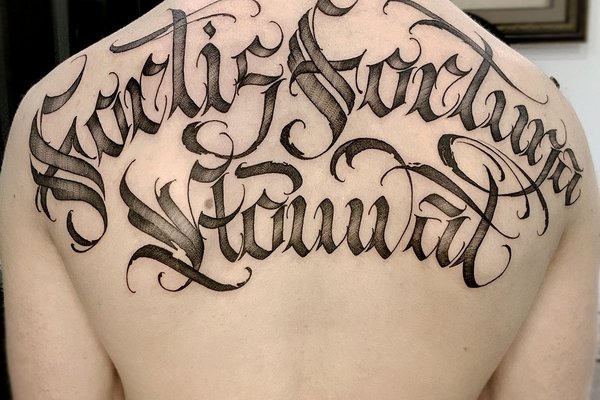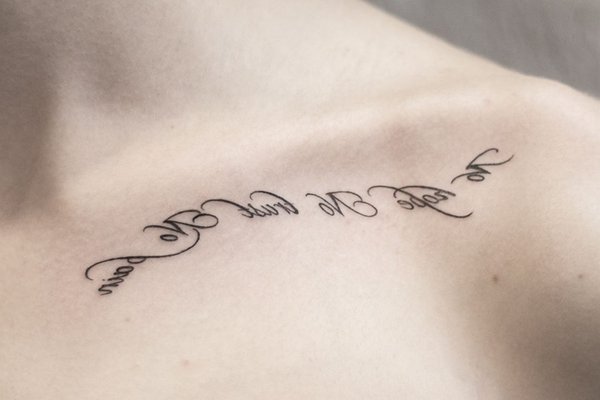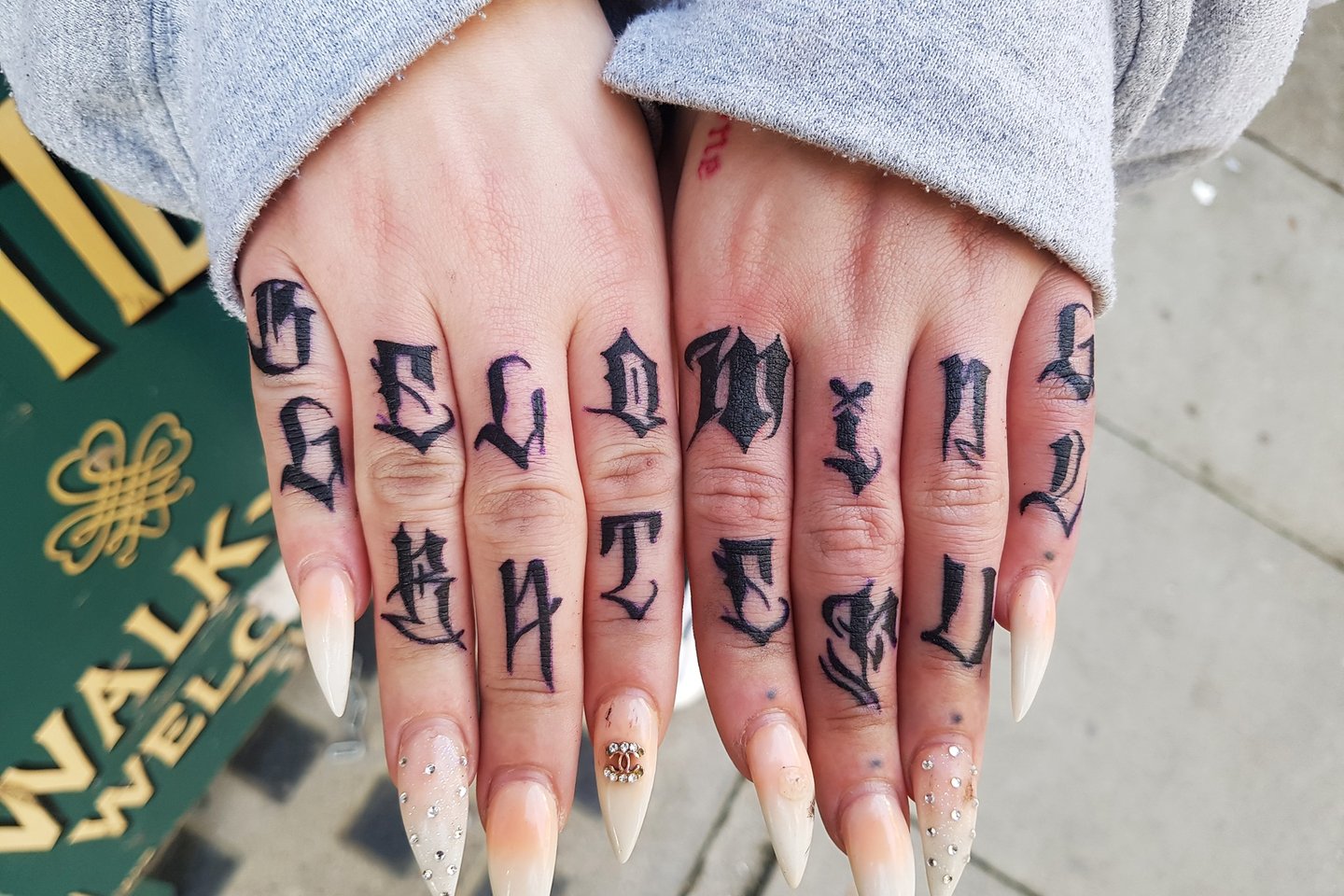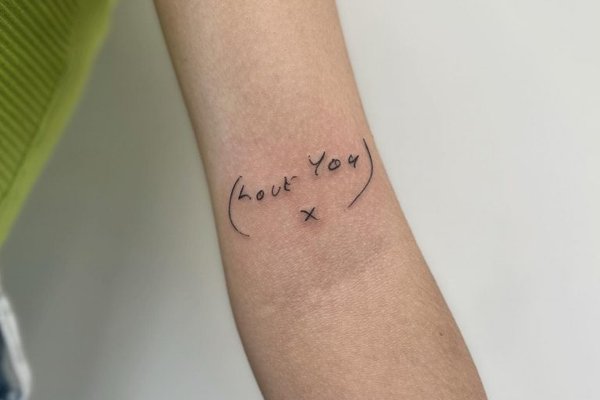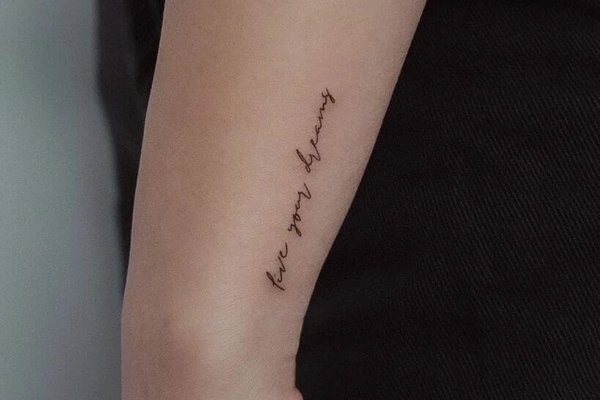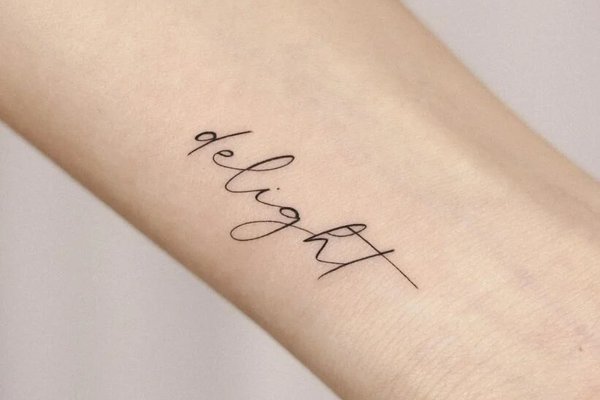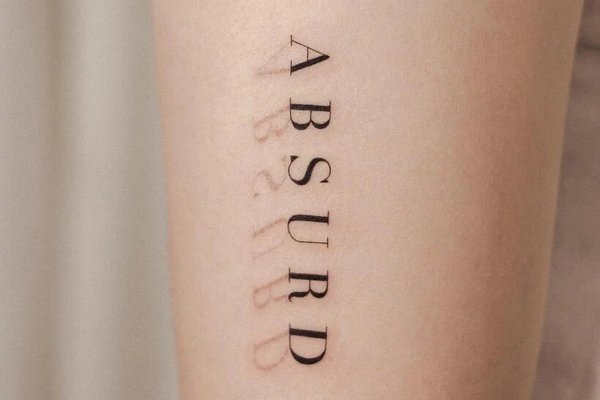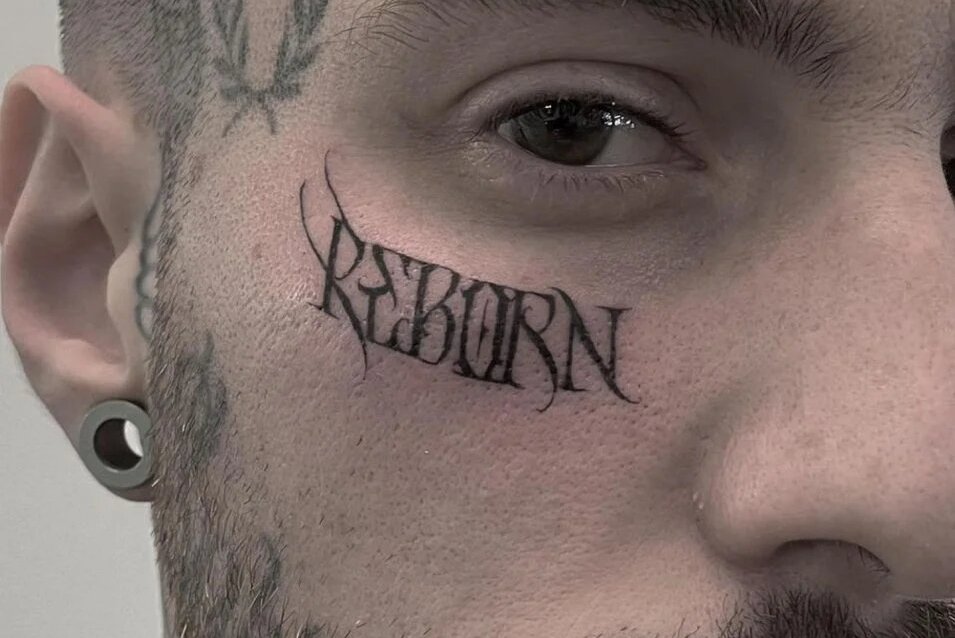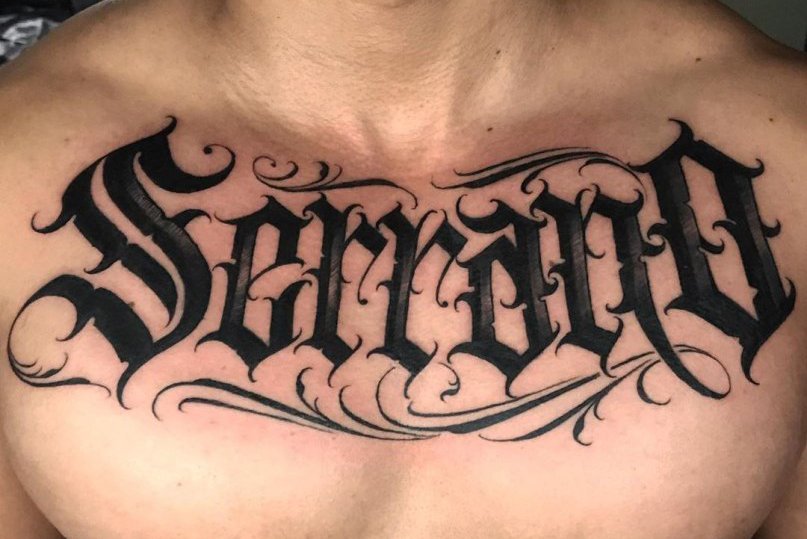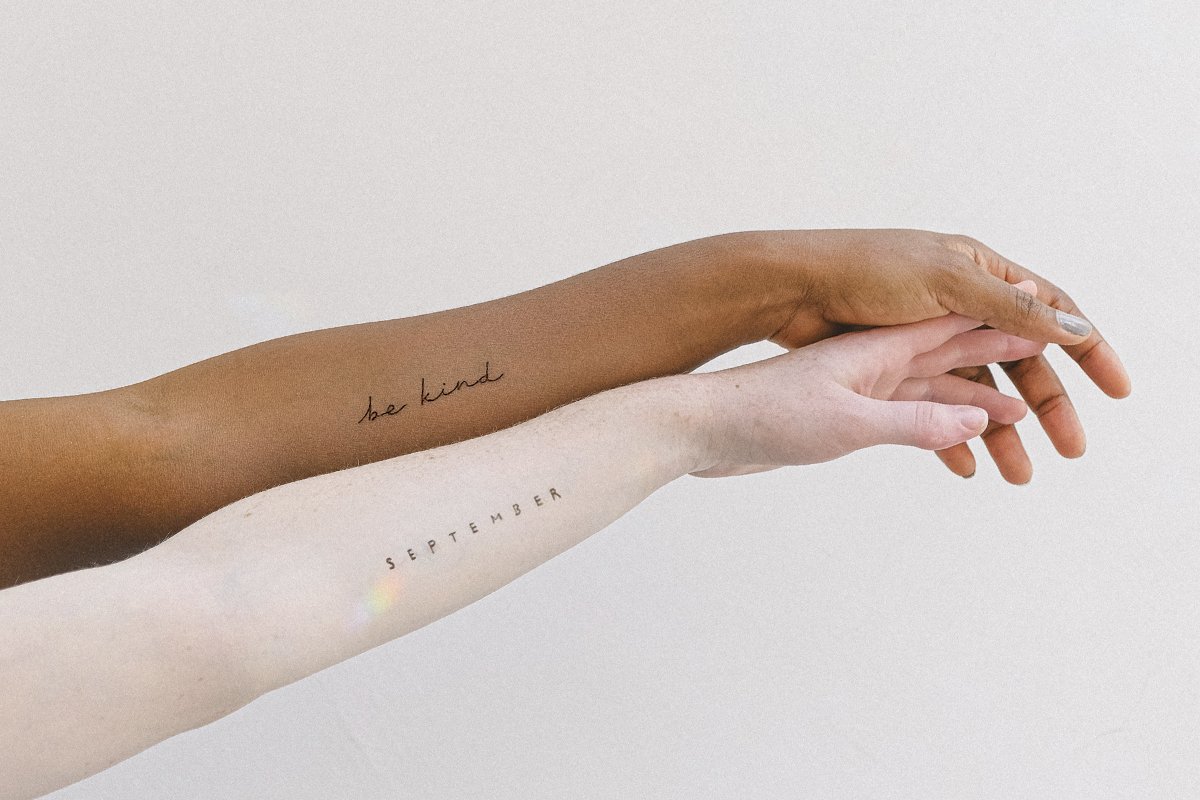
Czcionki do tatuażu online
Jednym z najczęstszych stylów w branży tatuażu jest nakładanie jakiegoś tekstu.
Wybór tekstu jest trudny, ale wybór samej czcionki będzie jeszcze trudniejszy. Biorąc pod uwagę mnóstwo możliwości, a także indywidualne podejście tatuatora do każdego klienta, można długo mówić o konkretnych rodzajach tatuaży.
Styl czcionki
Jak wybrać czcionkę do tatuażu?
Przede wszystkim, jeśli zdecydowałeś się na tekst, musisz wybrać odpowiedni projekt. Dodatkowo warto zastanowić się nad stylem samego klienta, który będzie odpowiadał jego stylowi, hobby, pracy, wartościom życiowym. Na podstawie wielu szczegółów można określić najlepszą opcję. Pamiętaj, że u nas możesz przeglądać online wszystkie czcionki do tatuaży, a także uzyskać pomoc i porady konsultanta online. Aby to zrobić, przejdź do odpowiedniej kategorii i rozważ oferowane opcje. Możesz także przejrzeć setki innych opcji w sieci, aby dowiedzieć się, jak tatuaż będzie wyglądał w miejscu, w którym zamierzasz go zastosować.
Rozmiar czcionki
Aby określić rozmiar czcionki, musisz określić dokładne położenie tekstu. Ustawiając go, możesz sobie wyobrazić inne opcje rozmiaru - szerokość i długość każdej litery. Tekst może składać się zarówno z małych liter, jak i zaczynać się od dużej litery, podkreślając nazwę lub miasto, kraj.
Kolor napisów
Jeśli zastanawiałeś się nad czcionkami do tatuażu i zdecydowałeś się na opcję, a także jesteś pewien tematu napisu, możesz rozważyć paletę kolorów.
Być może najlepszą opcją byłby czarno-biały tatuaż lub bardziej odpowiednie byłoby wykonanie tatuażu w jasnych kolorach. Możesz stworzyć kilka kolorów, łącząc je:
- Wykonaj jasną kreskę.
- Dodaj kolorowy cień.
- Wypełnianie liter może odbywać się z przejściami kolorystycznymi.
Jest to najlepsza opcja, aby uzyskać pożądany rezultat. Czcionki wybrane na stronie są wybierane online jako najlepsze i najbardziej skuteczne dla prawie każdego miejsca zastosowania. Sam styl tatuażu może być minimalistycznym, gotyckim lub graficznym. Sam wybierasz najlepszy styl dla swojego tatuażu, ale rady tatuażysty zawsze będą przydatne. Rozważ z nami czcionki do tatuażu, przemyśl projekt, wybierz kilka opcji i z góry przemyśl wszystkie szczegóły.
Popularne
miejsca na tatuaż
Miejsce na tatuaż to wybór klienta, jednak są popularne miejsca na nanoszenie czcionek.
Takie miejsca można uznać za przedramiona rąk, nóg, często są napisy na nadgarstkach, szyi, plecach. Wielu klientów uważa, że czcionki tatuażu powinny być wykonywane na klatce piersiowej, takie jak numer seryjny lub imię ukochanej osoby.
Preferencje czcionek
Dziewczyny bardziej lubią wyrafinowanie, wyrafinowanie linii, cienkie i lekkie czcionki. Jeśli mówimy o płci męskiej, preferowane są większe, odważniejsze i bardziej surowe napisy, z których większość ma obrys, być może w kolorze. Jednak te standardy nie zawsze są odpowiednie dla naszych klientów, biorąc pod uwagę, że większość z nich to ludzie o jasnym wyglądzie i dobrym guście.
Jak wybrać czcionkę do tatuażu?
Wybór czcionki do tatuażu jest równie ważny jak sam tekst. Odpowiednio dobrany styl liter może podkreślić charakter napisu, jego znaczenie oraz dopasować projekt do miejsca na ciele.
Delikatne czcionki na tatuaż są często wybierane do imion, dat oraz krótkich sentencji, natomiast ozdobne czcionki sprawdzają się przy większych projektach i bardziej dekoracyjnych kompozycjach.
Przed wykonaniem tatuażu warto porównać kilka różnych wariantów. Generator czcionek do tatuażu pozwala sprawdzić, jak ten sam napis wygląda w stylu gotyckim, kaligraficznym, minimalistycznym lub inspirowanym odręcznym pismem. Dzięki temu łatwiej znaleźć rozwiązanie dopasowane do własnych preferencji.
Popularne są również czcionki do tatuażu z cyframi, wykorzystywane przy ważnych datach, rocznicach czy cyfrach rzymskich. Niezależnie od wybranego stylu warto pamiętać, że najlepsza czcionka do tatuażu powinna być nie tylko efektowna, ale również czytelna przez wiele lat.
- Jakie są najładniejsze czcionki na tatuaż?
- Do najpopularniejszych należą czcionki kaligraficzne, gotyckie, Fine Line oraz style inspirowane odręcznym pismem. Ostateczny wybór zależy od długości napisu i oczekiwanego efektu.
- Jakie delikatne czcionki na tatuaż są obecnie modne?
- Obecnie dużą popularnością cieszą się minimalistyczne czcionki Fine Line, cienkie litery oraz subtelne napisy wykonywane prostym, eleganckim krojem pisma.
- Czy można skopiować wygenerowany napis do tatuażu?
- Do dat najczęściej wybierane są czytelne czcionki klasyczne, kaligraficzne oraz cyfry rzymskie, które od lat należą do najpopularniejszych motywów w tatuażach tekstowych.
- Czy generator czcionek do tatuażu pokazuje rzeczywisty wygląd tatuażu?
- Generator prezentuje poglądowy wygląd napisu. Ostateczny efekt zależy od wielkości projektu, miejsca wykonania oraz techniki pracy wybranego tatuatora.